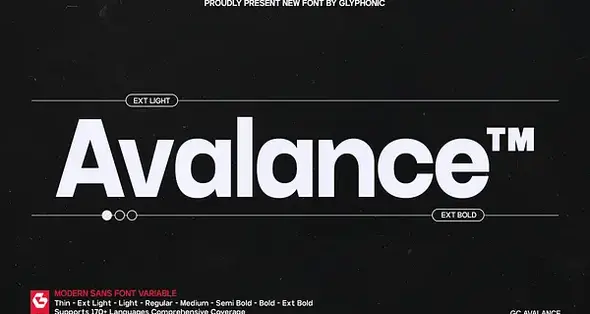
• GC Avalance – Neo Modern Typeface
فونت انگلیسی مدرن سنس سریف
خانواده فونت GC Avalance یک تایپ‌فیس سان‌سریف (Sans Serif) معاصر است که با تمرکز بر دقت، تعادل و انعطاف‌پذیری طراحی شده است. این فونت با ساختار هندسی تمیز و تناسبات نرم خود، لحنی جسورانه و در عین حال ظریف (Bold yet Refined) را ارائه می‌دهد که به طور یکپارچه با هر دو فضای طراحی دیجیتال و چاپ سازگار است.
GC Avalance برای وضوح، چه در حالت متحرک (Motion) و چه در حالت ثابت طراحی شده و پیچیدگی و ظرافت مدرنی را به هر پروژه خلاقانه‌ای می‌بخشد.
کاربردها:
این فونت برای برندسازی (Branding)، صفحه‌آرایی و نشریات، رابط‌های کاربری (UI) و هویت‌های بصری جسورانه ایده‌آل است. GC Avalance زیبایی‌شناسی مدرن و بااعتمادبه‌نفسی را بدون قربانی کردن خوانایی به نمایش می‌گذارد. تمام وزن‌ها—از نازک (Thin) تا خیلی ضخیم (Extra Bold)—با دقت تنظیم شده‌اند تا هم در تیترها و هم در متن‌های طولانی (Body text) هماهنگی و تأثیرگذاری بالایی داشته باشند.
ویژگی‌های کلیدی:
• فونت متغیر (Variable Font): شامل وزن‌های پیوسته از Thin تا Extra Bold.
• کاراکترها: شامل حروف بزرگ و کوچک، اعداد و علائم نگارشی.
• ساختار: طراحی هندسی نئو-مدرن (Neo-Modern Geometric).
• پشتیبانی زبانی: پشتیبانی از بیش از ۱۷۰ زبان (Multilingual).
با GC Avalance، وضوح، ساختار و نگاهی رو به آینده را به تایپوگرافی خود هدیه دهید.
GC Avalance – Neo Modern Typeface is a contemporary sans serif font family crafted for precision, balance, and versatility. With its clean geometric structure and smooth proportions, GC Avalance delivers a bold yet refined voice that adapts seamlessly across digital and print design. Designed for clarity in motion and stillness, it brings modern sophistication to any creative project.
Perfect for branding, editorial layouts, interfaces, and bold visual identities, GC Avalance embodies a confident modern aesthetic without sacrificing readability. Each weight—from Thin to Extra Bold—has been carefully tuned for harmony and impact, making it ideal for both headlines and body text.
Features:
- Variable Font (Thin–Extra Bold)
- Uppercase & Lowercase
- Numbers & Punctuation
- Neo-Modern Geometric Construction
- Multilingual Support (170+ Languages)
Bring clarity, structure, and a forward-thinking edge to your typography with GC Avalance – Neo Modern Typeface.